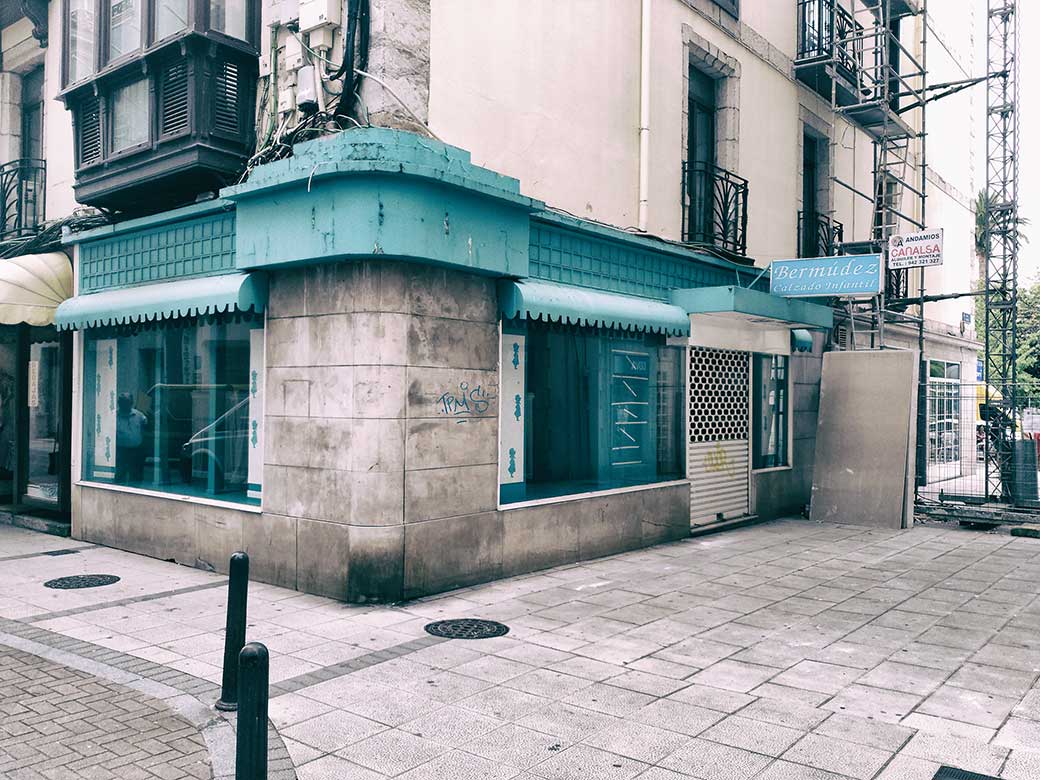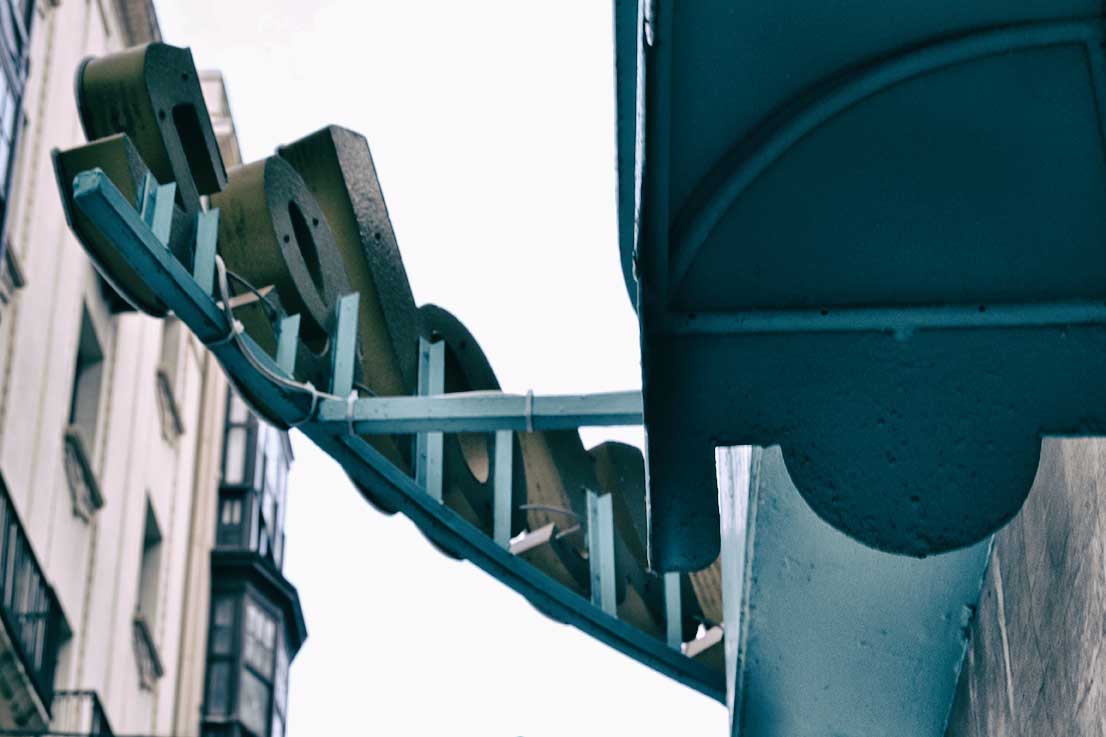
Calzados Bermudez
Fue un Martes y 13 del mes de agosto de 1966, cuando esta mítica zapatería infantil abrió sus puertas. Durante 49 años calzó a muchos niños de Santander. Pero con motivo de la nueva ley de rentas, al igual que otros negocios que había sobrevivido en el centro de la ciudad, en octubre de 2015 cerró. Hoy solo queda ese color característico azul en la fachada. El rótulo, con esa tipo tan característica y como estaba instalado que había en la esquina ha desaparecido. Solo queda un pequeño cartel que recuerda de allí hubo un negocio.
Estado actual (Julio 2016)